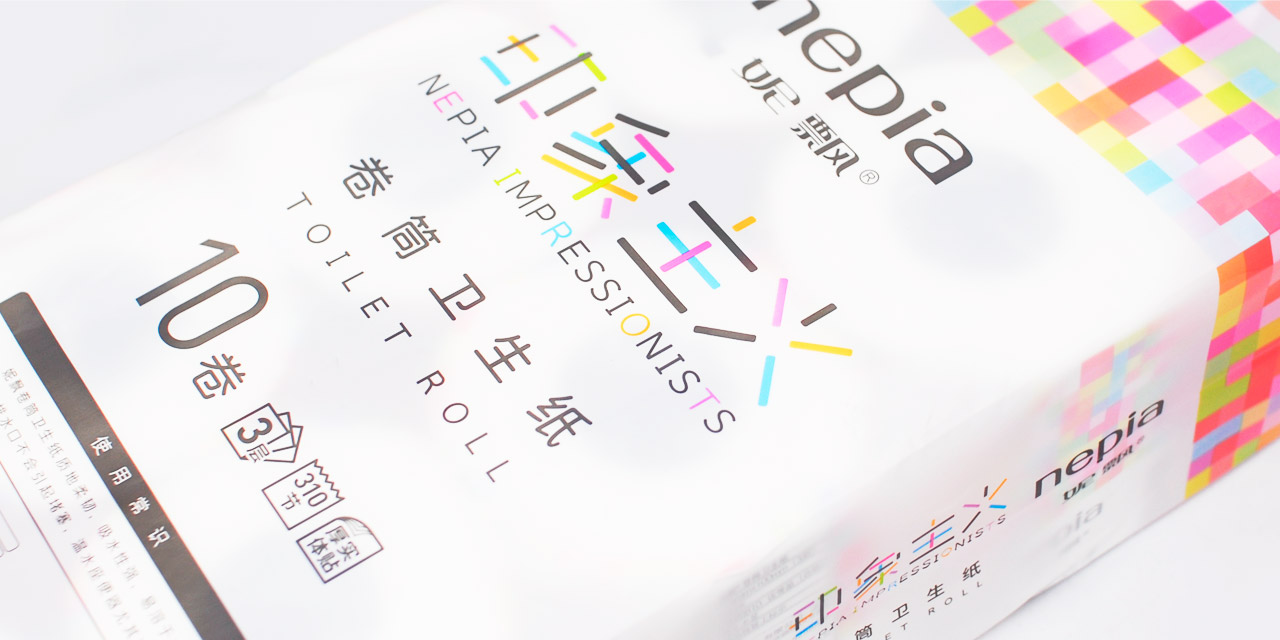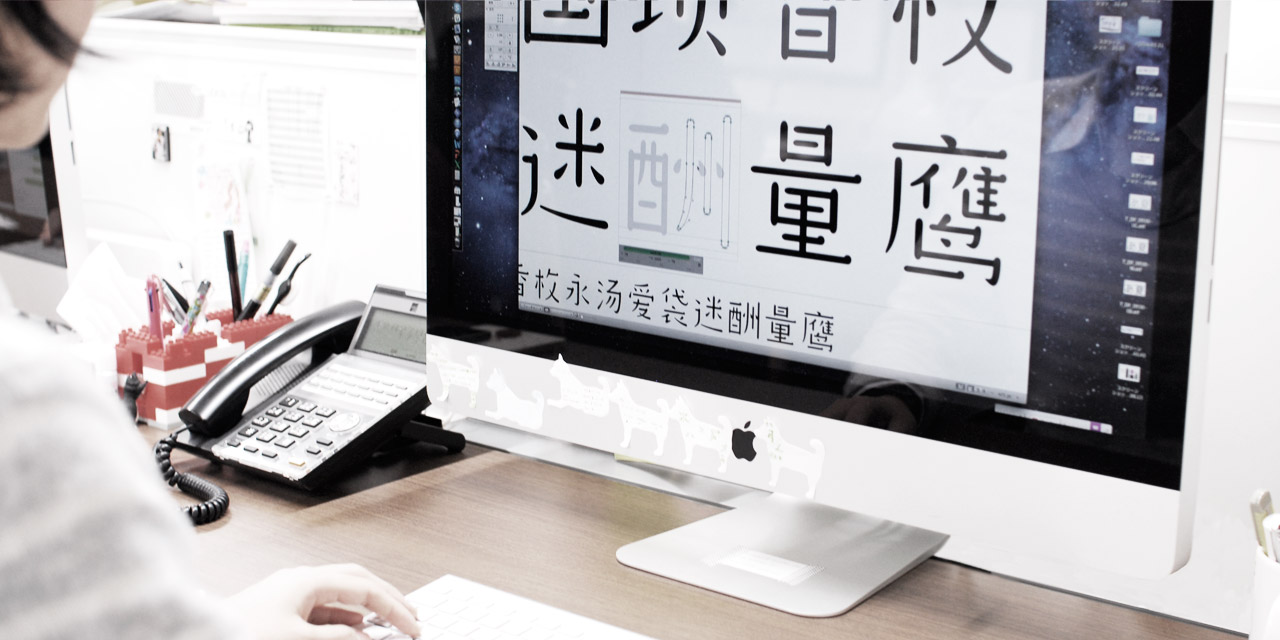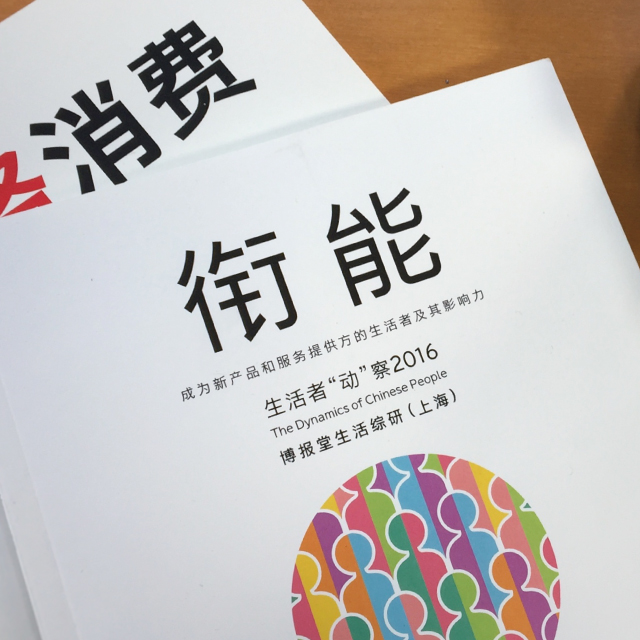
• CASE
上海妮飘「印象主义」
• 理杏美琉体,不仅保留着基础字体的实用性,同时将点、撇、捺等笔画如同行云流水般进行了设计调整,使字体显得更为纤美。文章更将因其宽大的字怀与秀美易读的字形,演绎出如诗般优雅的韵味。从标题到正文都可通过这一系列,构成清新流畅的篇章。
理杏美琉体
(4字体)
• 理杏黑体共有7种粗细可供选择,由于其宽敞、不显拘谨的字形,不仅易于阅读,更给人以落落大方的印象。字与字的组合稳重、优美、品味,可运用在平面广告、杂志的标题、正文、注脚以及网页、产品包装上,是一款可以广泛活跃在各种场合的基础字体。
理杏黑体
(7字体)
• CASE
博报堂生活综研(上海)
「出格消费」
• 理杏葆元体,圆润饱满且坚定挺拔的笔画,让文字更内在生动,充满生机,作为个性鲜明的标题字使用表现力更佳。
理杏葆元体
(1字体)
• 理杏震黑体因其苍劲有力的笔画设计而得此名,与同类字体相比,通过省略提勾的设计,使其在文字表现上更为简约时尚,作为标题体被广泛应用于各品牌的宣传广告中。同时,理杏震黑体除了粗体的B以外,在此基础上增加了稍细的M,以满足不同需求。
理杏震黑体
(2字体)
• CASE
协和发酵KIRIN
品牌手册
• CASE
上海妮飘「聚能吸 厨房用纸」
• 理杏美玲宋体,继承宋体横细竖粗的特点,用圆形装饰笔画尾端,给人以与普通宋体不同的柔雅印象。理杏美玲宋体除了标准粗细的R以外,还有纤细的L与稍有力度的M,是演绎高雅的包装设计,或是表达简洁的文字效果时的不二之选。
理杏美玲宋体
(3字体)